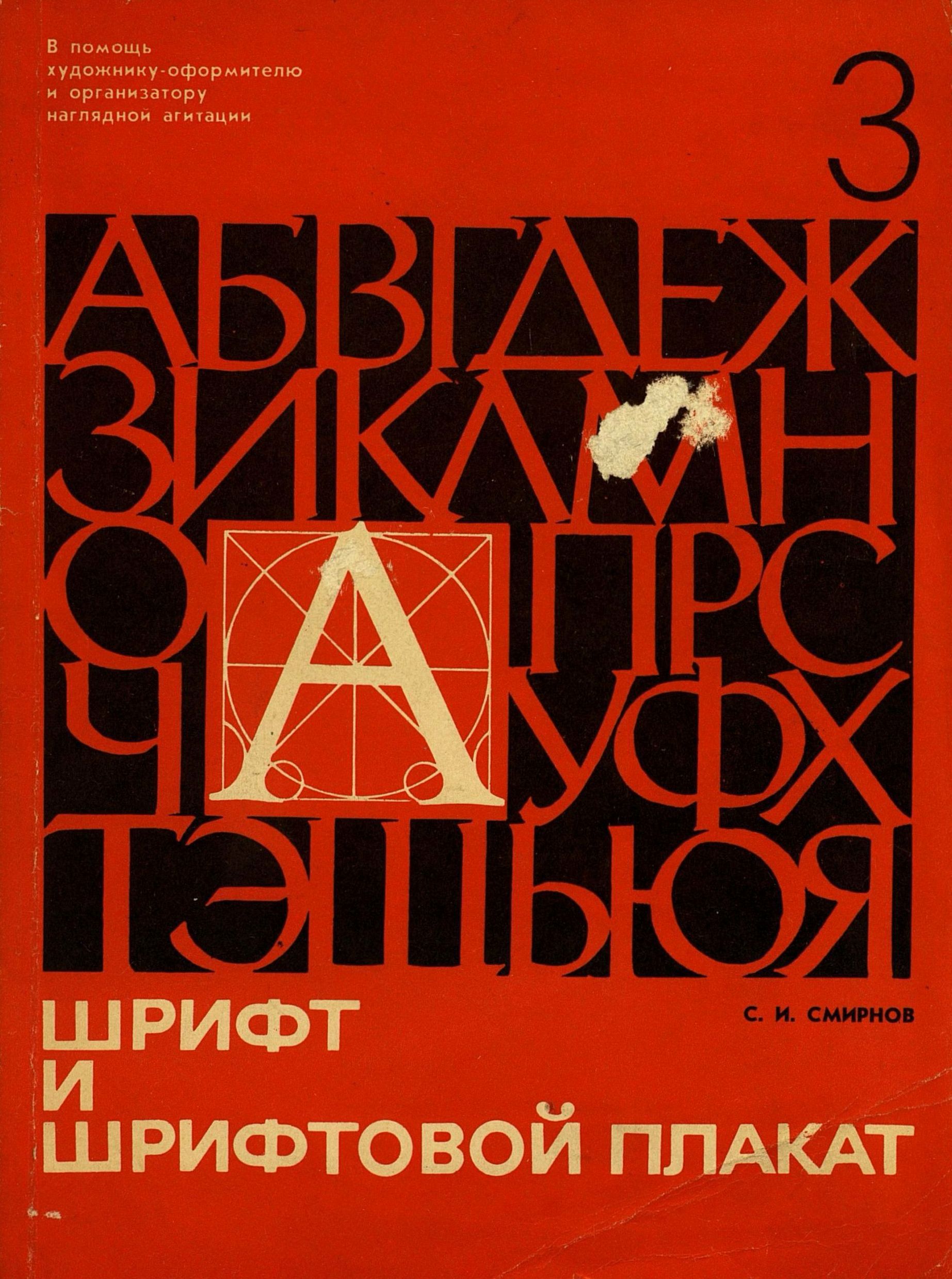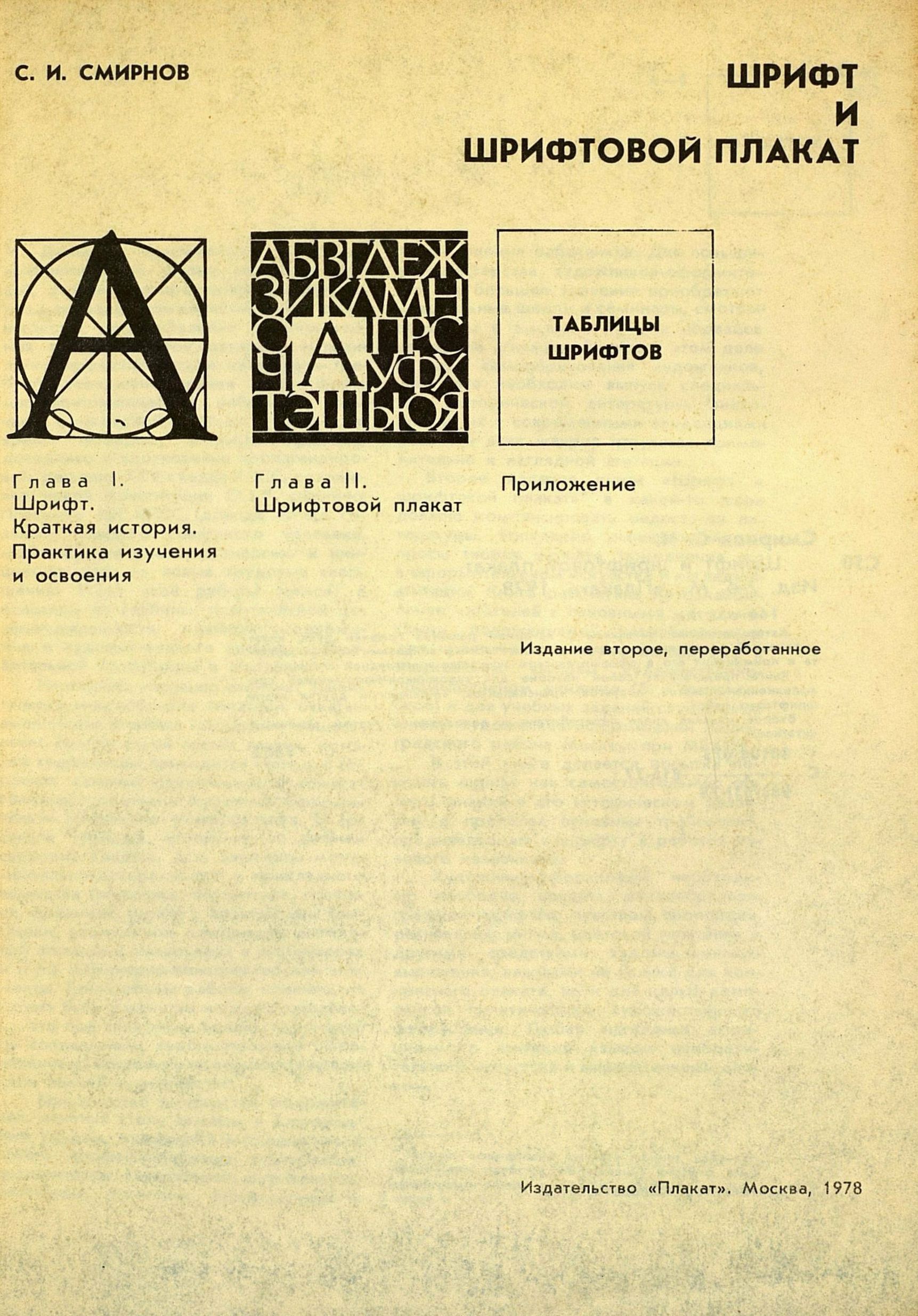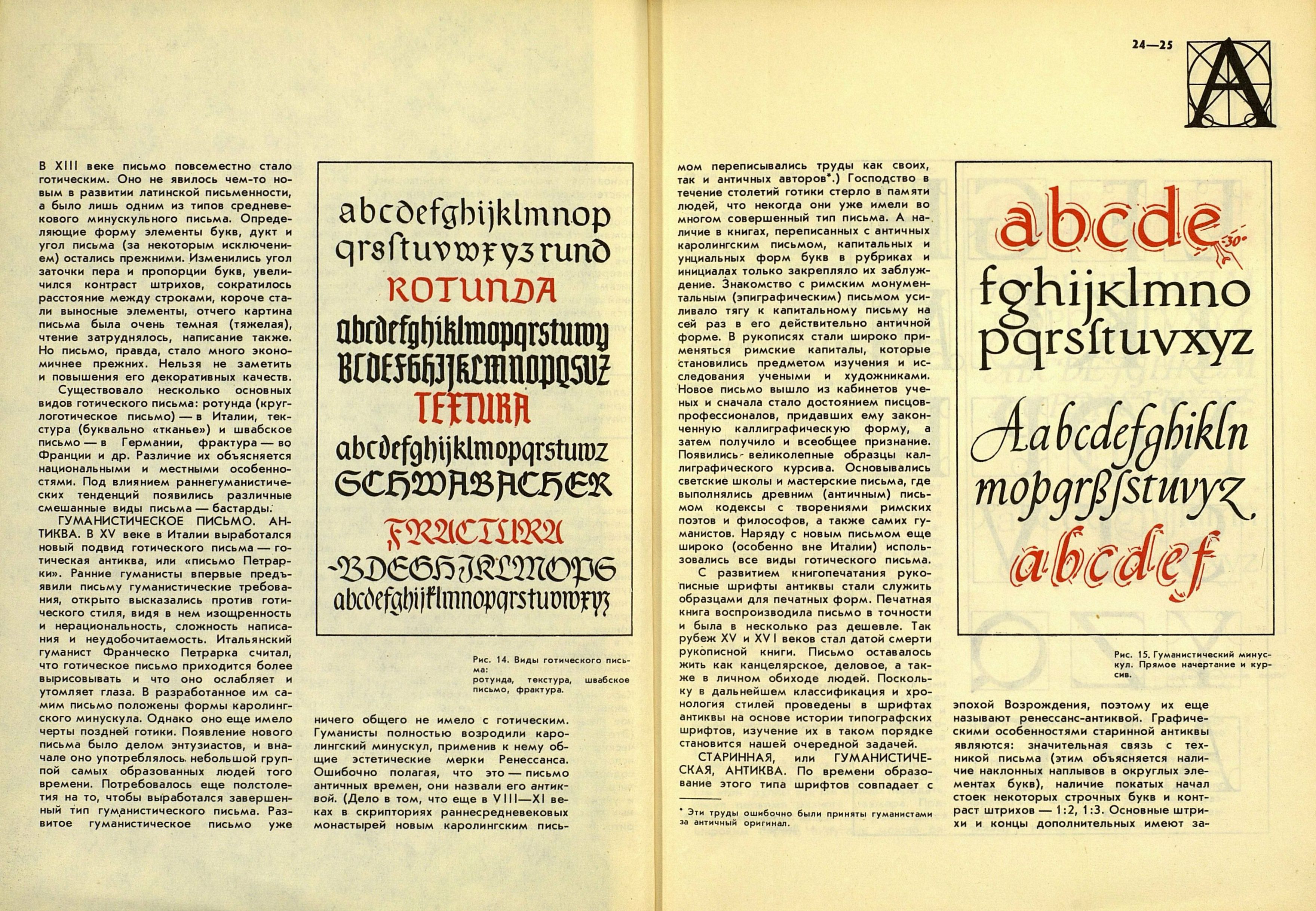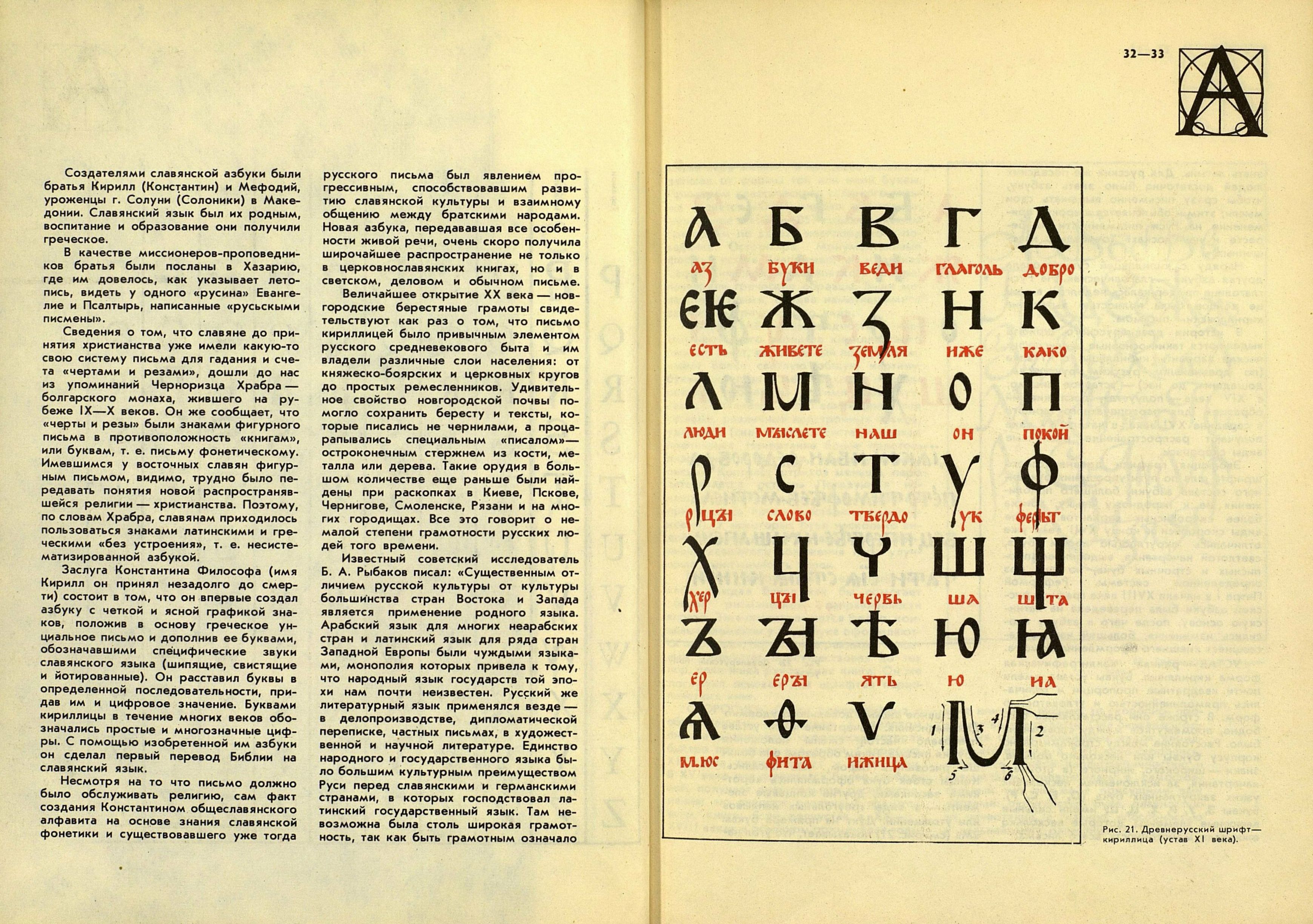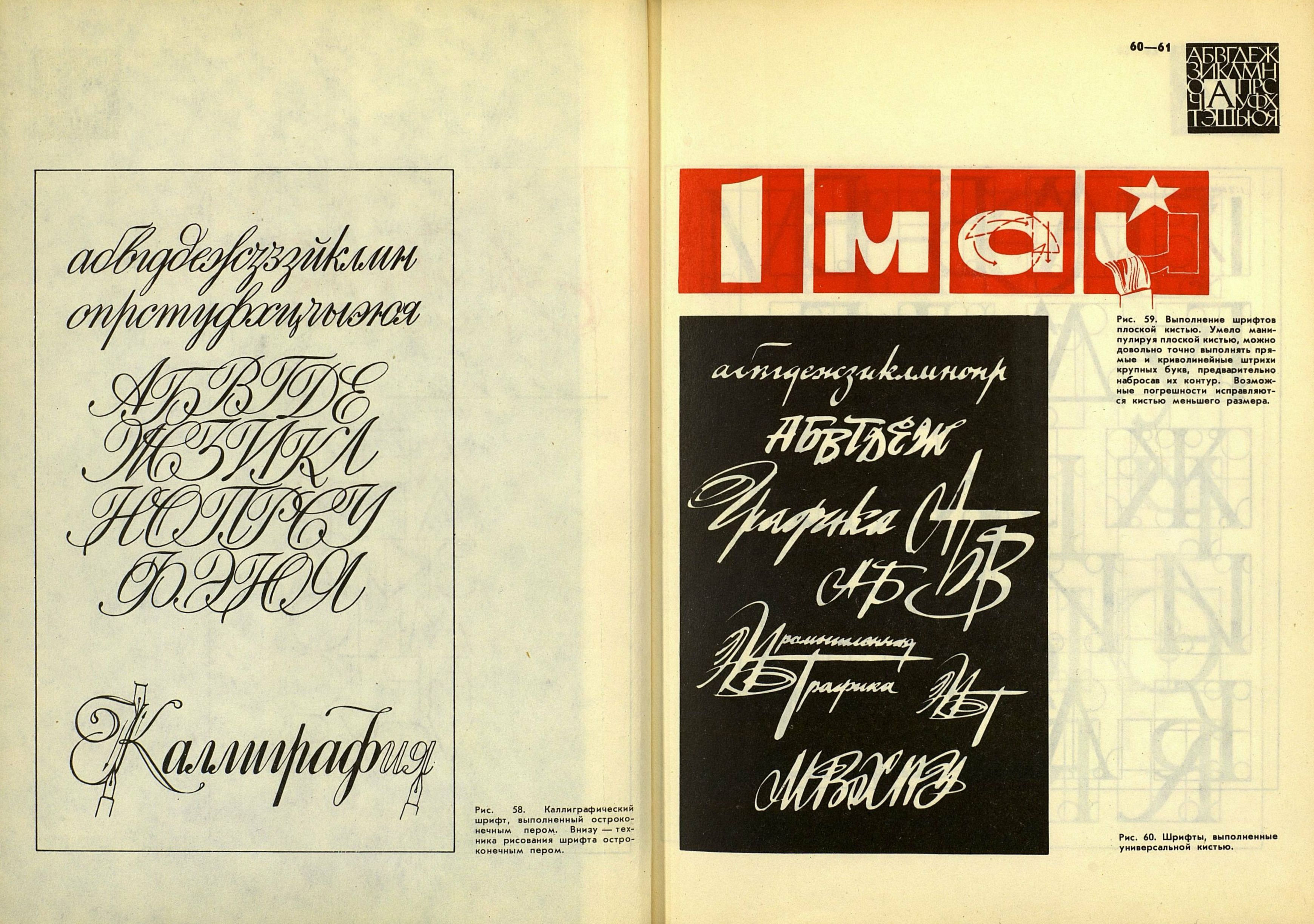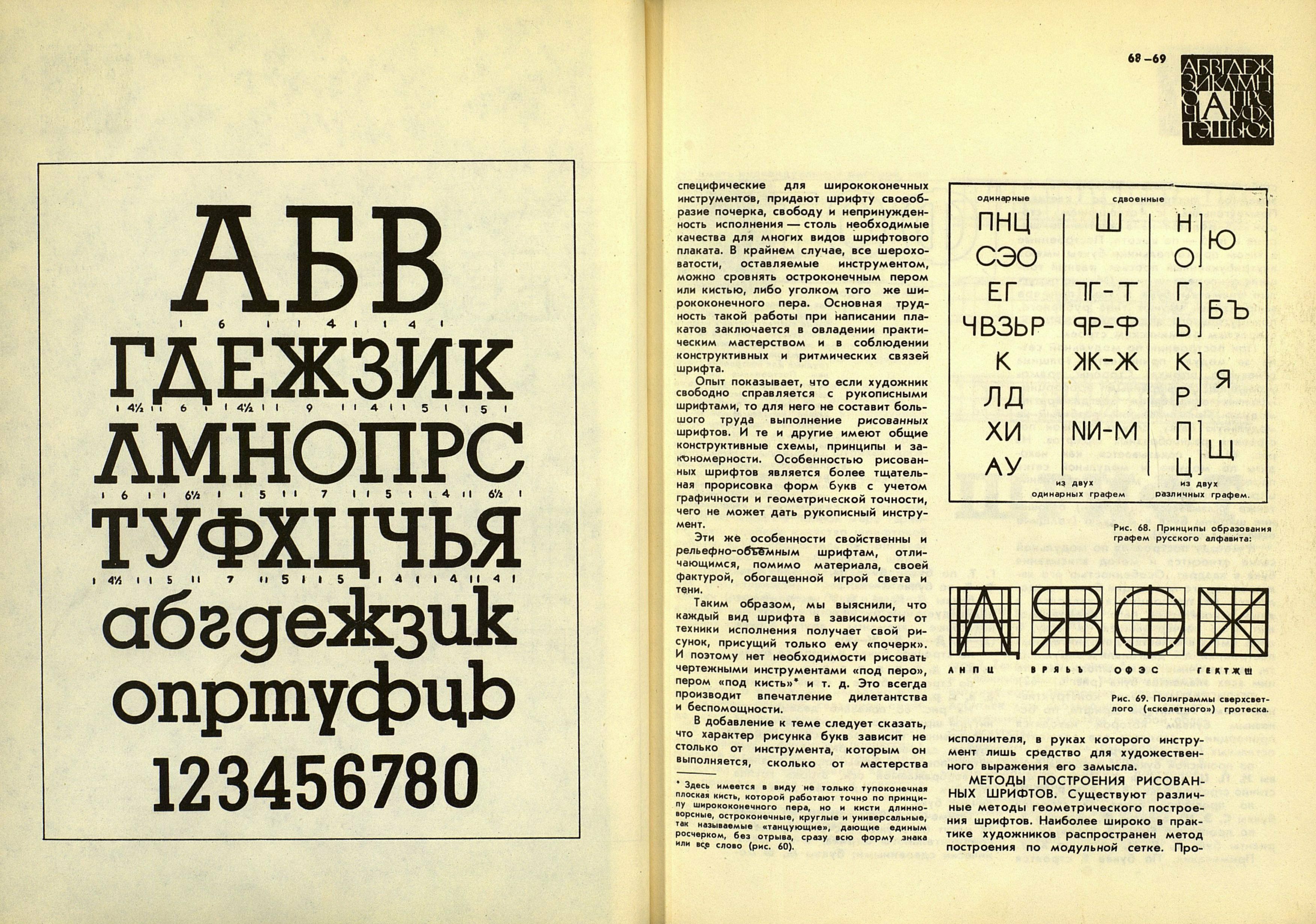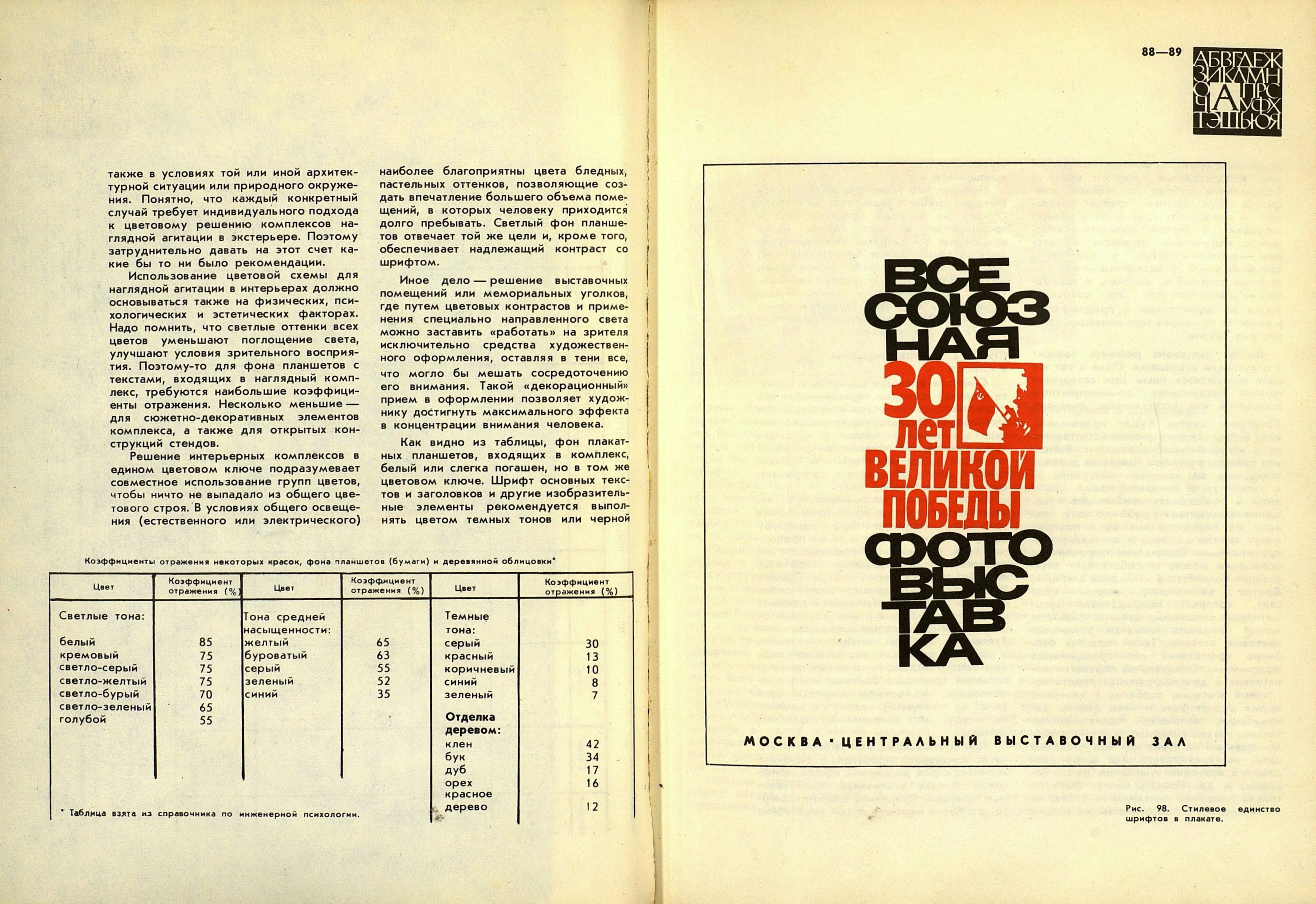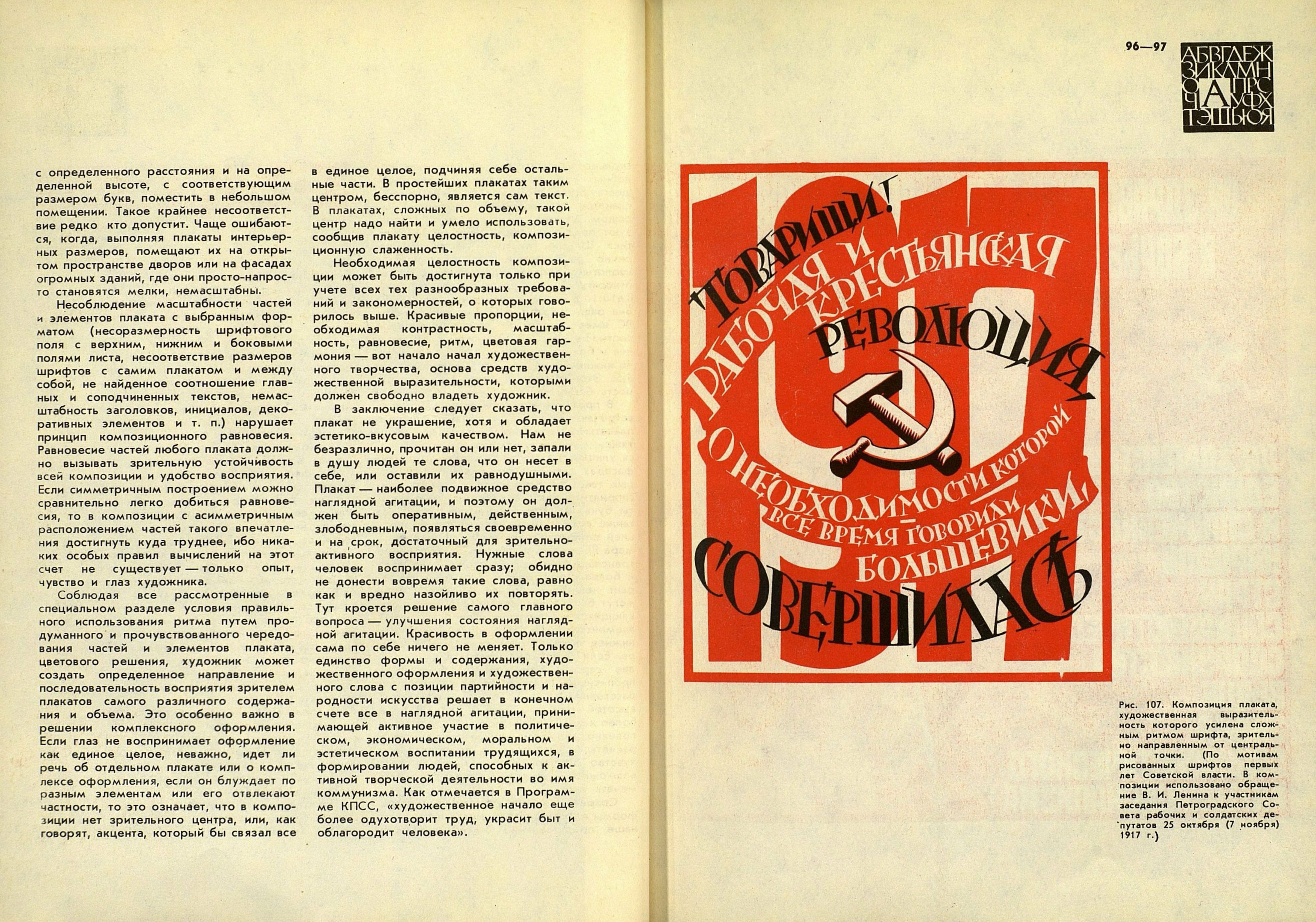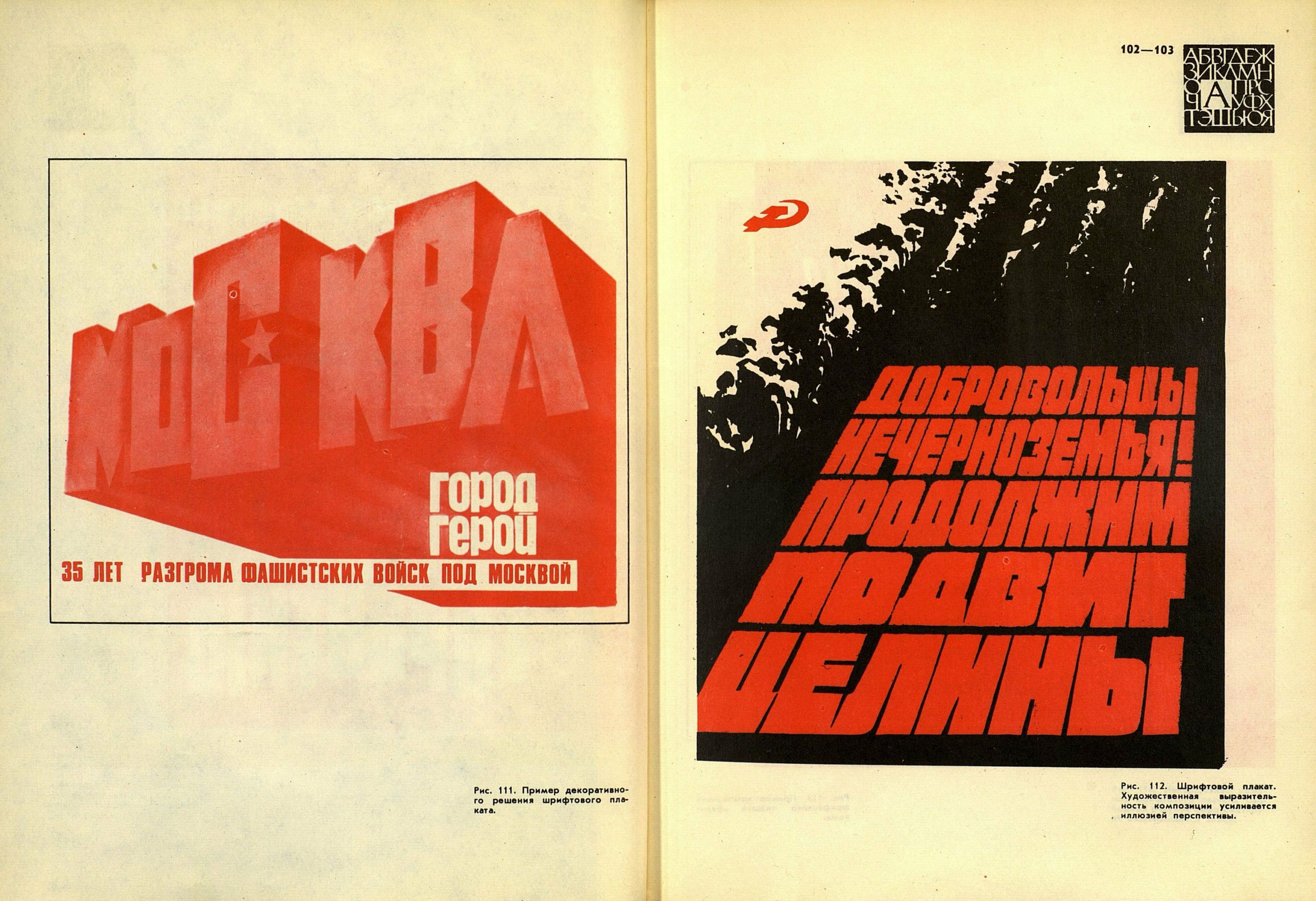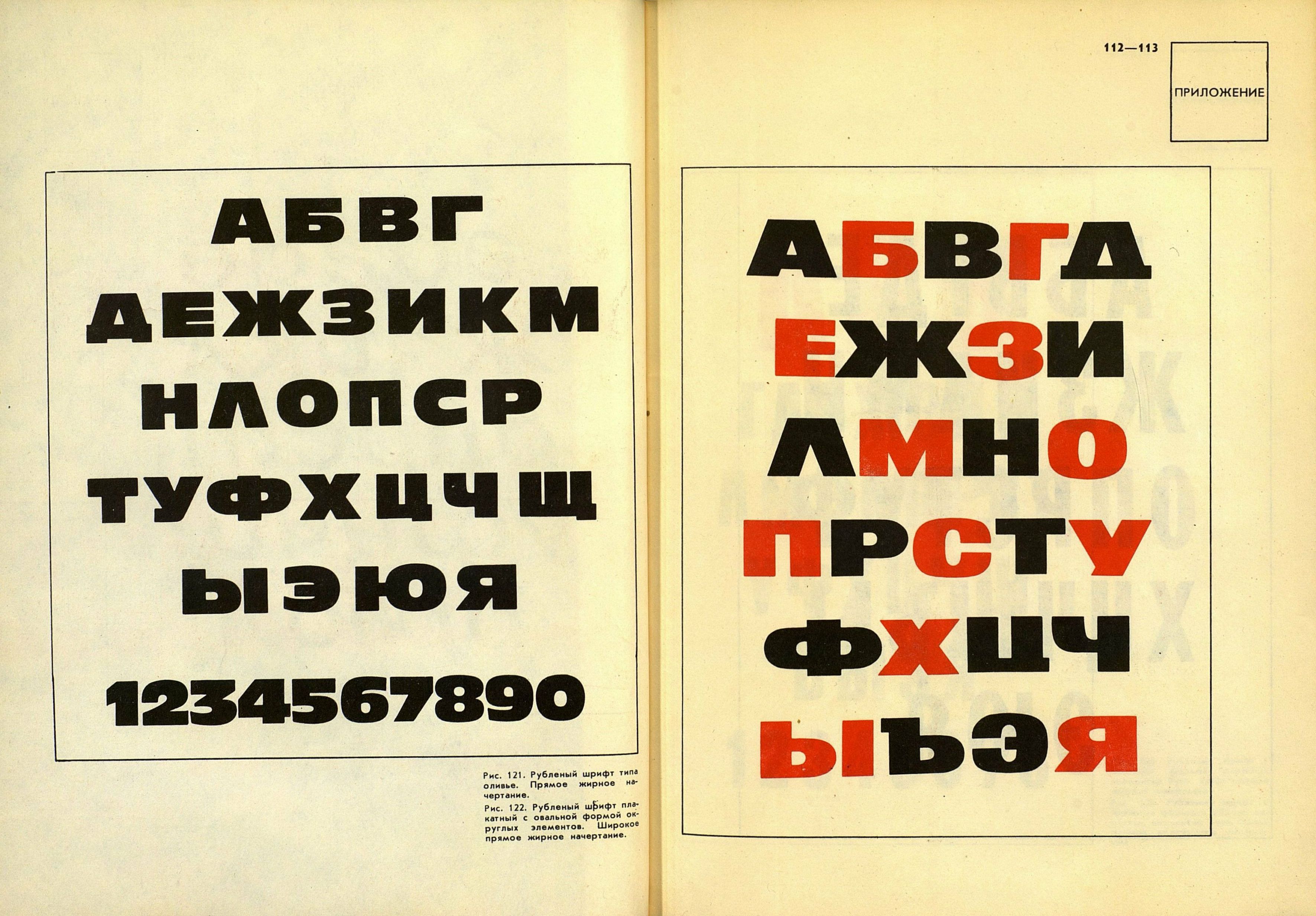
Смирнов С. И. Шрифт и шрифтовой плакат. — Изд. 2-е. — Москва, 1978 ![]() Шрифт и шрифтовой плакат / С. И. Смирнов. — Издание 2-е, переработанное. — Москва : Плакат, 1978. — 144 с. : ил. — (В помощь художнику-оформителю и организатору наглядной агитации. [Выпуск] 3).[Аннотация]
Автор знакомит читателей с историей развития графики букв, классификацией современных шрифтов, с некоторыми вопросами теории шрифта и применения его в оформительском искусстве и наглядной агитации.
Книга представляет собой пособие для художников-оформителей при выполнении плакатов, лозунгов, транспарантов, «Молний» и других видов шрифтовых работ.
Второе издание книги переработано и дополнено с учетом замечаний читателей.
ОТ АВТОРА
Динамизм современной общественно-политической жизни советских людей, дальнейшее продвижение вперед в решении задач коммунистического строительства, осуществление величественных планов десятой пятилетки — пятилетки эффективности и качества — требуют совершенствования всех форм массово-политической работы, в том числе и наглядной агитации. В настоящее время наглядная агитация призвана доходчиво и вдохновенно пропагандировать решения XXV съезда КПСС, положения новой Конституции СССР, решения Пленумов ЦК КПСС, доводя их до сознания каждого советского человека, мобилизуя творческую энергию и инициативу масс на новые трудовые свершения. Успех этой работы зависит в основном от глубины, политической целенаправленности, идейного содержания и художественного уровня изобразительной пропаганды и агитации.
Наглядную агитацию отличает значительное многообразие тематики, охватывающей все стороны трудовой и общественно-политической жизни людей, которое художникам приходится наглядно отражать самыми различными художественными средствами. Художник-оформитель — профессия универсальная. В арсенале средств, которыми он должен свободно владеть, есть элементы монументально-декоративного и прикладного искусства (живопись, скульптура, графика, орнамент, шрифт), архитектуры (выставки, размещение комплексов наглядной агитации в интерьерах и экстерьерах и т. п.), инженерно-конструкторские элементы. Такой объем работы, конечно, не может быть рассчитан на одного человека, это под силу лишь коллективу людей со специальным художественным образованием, постоянно совершенствующих свои знания и мастерство.
Большинство энтузиастов оформителей, занятых столь важным и благородным трудом, нуждаются в поддержке и совете профессиональных художников, архитекторов, литераторов, журналистов, партийных, советских, профсоюзных и хозяйственных работников. Для повышения мастерства художников-оформителей все большее значение приобретают специальные школы и семинары, смотры-конкурсы и выставки лучших образцов наглядной агитации. Велика в этом деле и роль самообразования художников, для чего необходим выпуск специальной методической литературы, знакомящей их с современными тенденциями развития всех жанров искусства применительно к наглядной агитации.
Второе издание книги «Шрифт и шрифтовой плакат»* в какой-то мере должно компенсировать недостаток литературы, популярно освещающей вопросы теории шрифта, применения его в оформительском искусстве и наглядной агитации. Книга рассчитана на ознакомление читателей с основными методическими положениями, разработанными для практического курса по шрифту в Московском высшем художественно-промышленном училище (б. Строгановское) и для учебных заданий слушателям школы художников-оформителей Ленинградского района Москвы при МВХПУ.
* Термин «шрифтовой плакат» принят нами условно для удобства обозначения разного рода шрифтовых работ: призывов, «Молний», информаций и т. п.
В этой книге делается попытка показать шрифт как самостоятельную область знаний в его историческом развитии, в пределах основных требований, предъявляемых к шрифту в работах разового назначения.
Художнику-оформителю необходимо свободно владеть разнообразием графики шрифтов, чувством пропорции, равновесия, ритма, цветовой гармонии и другими средствами художественного выражения, важными не только для конкретного плаката, но и для целых комплексов политического художественного оформления. Любая наглядная агитация — это агитация языком изобразительного искусства и выразительным словом.
Графическая выразительность слова достигается образностью шрифта, ритмическим строем и целостностью шрифтовой композиции. Шрифт проходит через все средства наглядной агитации и в зависимости от тематики должен иметь такой рисунок, который наиболее точно передает настроение: пафос и романтику, призыв и спокойное напоминание, лирику, ассоциацию, юмор, сатиру и т. д. Сюжетная и декоративная стороны плакатов не рассматриваются, так как это не входит в тему нашей книги.
Данное пособие состоит из двух разделов. Первый посвящен истории латинского и русского шрифтов. Методологическая структура этого раздела преследует цель ознакомить художника в краткой форме с основными теоретическими взглядами на вопросы эволюции графики букв в историческом плане и показать, как можно научиться, не боясь «авторитета старины», воспроизводить те стили письма, которые явились как бы этапными в формировании графики современного шрифта. При этом художник должен не слепо копировать те или иные стили, а уметь осмысленно и свободно воспроизводить их лучшие формы, овладевая техникой работы ширококонечными перьями и другими шрифтовыми орудиями.
Умение свободно владеть техникой письма и рисования ширококонечными инструментами художнику необходимо еще и потому, что исторические стили латинской и русской систем письма, а точнее, их каллиграфические варианты* в прошлом выполнялись подобными же инструментами с тупым срезом (тростниковые, птичьи и даже бронзовые перья, найденные при раскопках Помпеи). Генетическая связь рукописной техники с печатными формами шрифтов вообще никогда не прерывалась. Рассматривая типографские шрифты, например старинной антиквы (см. таблицы), мы видим характерное соотношение штрихов в буквах, те же пропорции, наклоны округлых элементов, покатости в начале стоек строчных букв, т. е. все те графические особенности, которые достались им «в наследство» от перовой техники.